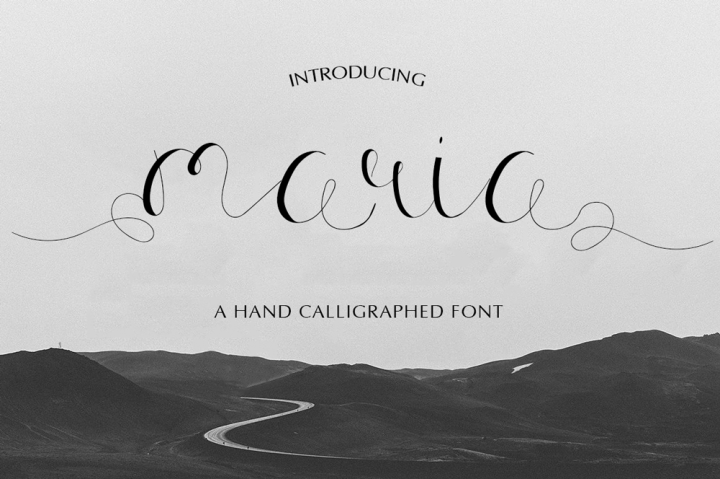
Maria Calligraphy Font – Download Grátis
A Maria Calligraphy Modern é uma fonte tipográfica moderna com traços script que busca transportar um estilo sofisticado e descontraído. Este design foi criado para aqueles que valorizam a elegância na literatura digital, permitindo personalizar textos de maneira única e arrojada sem perder o equilíbrio visual característico da escrita clássica. Uma fonte ideal para quem busca uma transição suave entre o tradicional e o contemporâneo, Maria Calligraphy Modern oferece a oportunidade de dar um toque diferenciado aos seus projetos digitais. Com sua disposição fluida e estilo moderno, esta fonte é perfeita tanto para gráficos de texto profissionais quanto para mensagens pessoais, garantindo sempre uma apresentação de alta qualidade e confortável para a leitura.